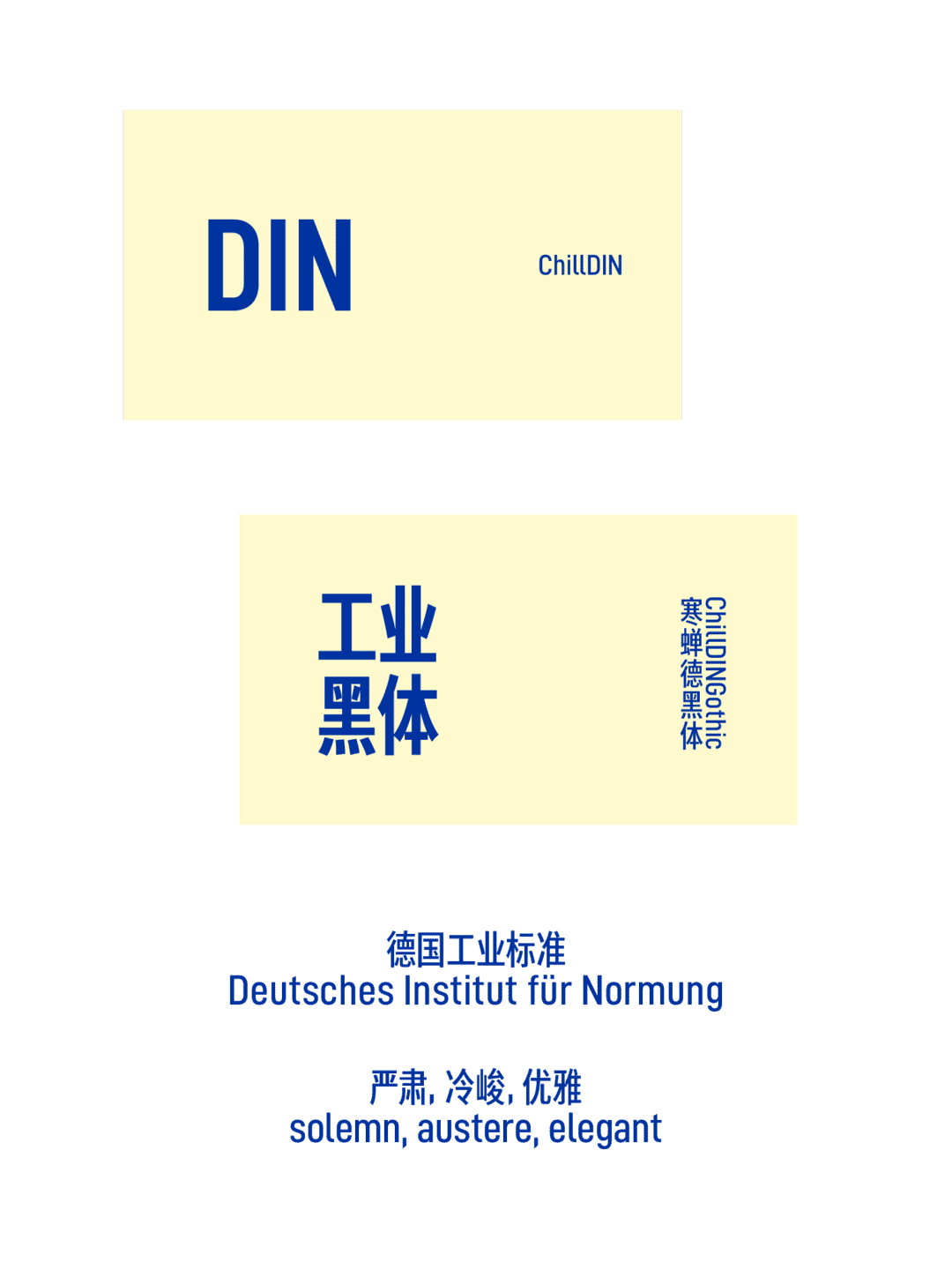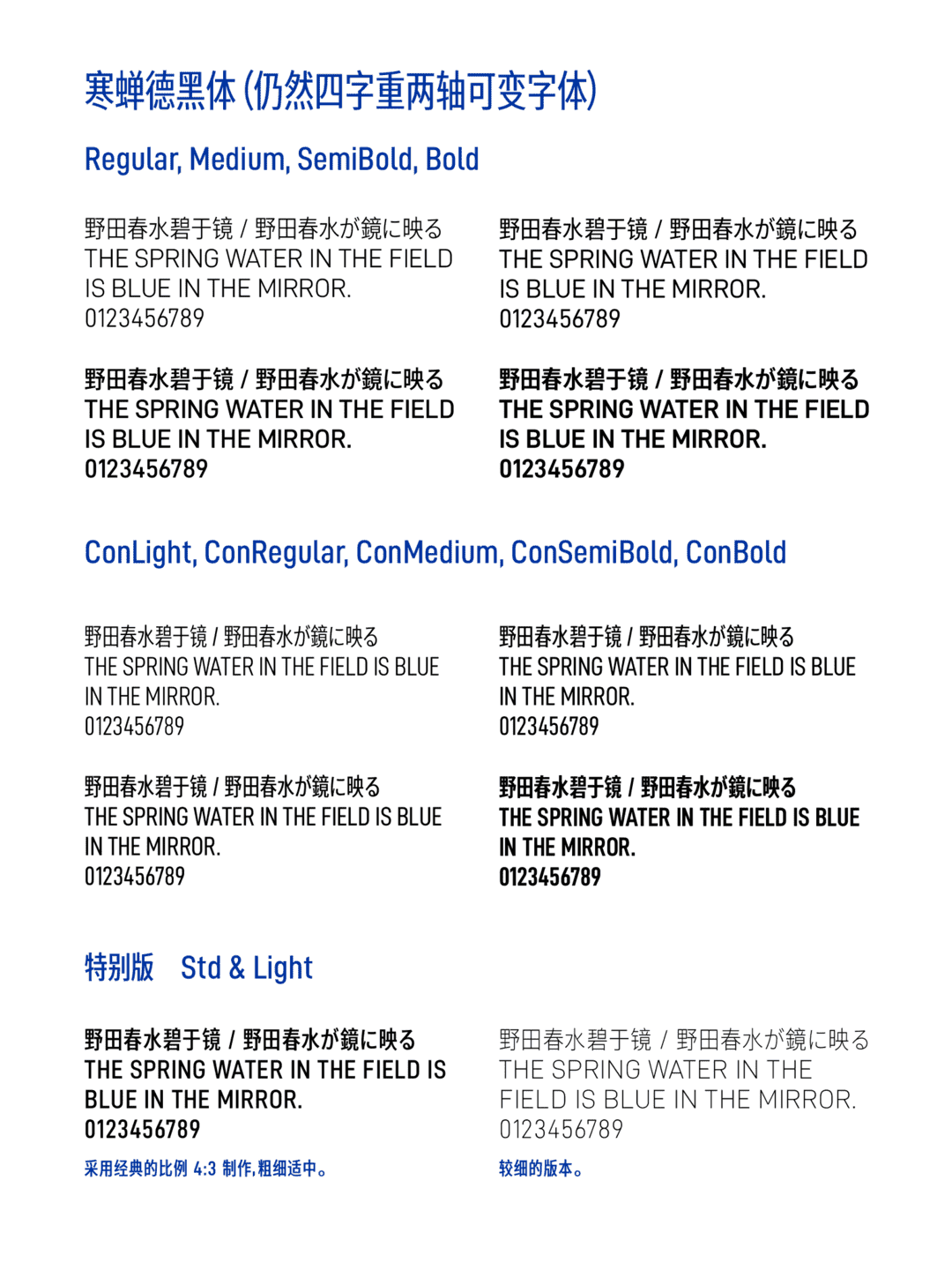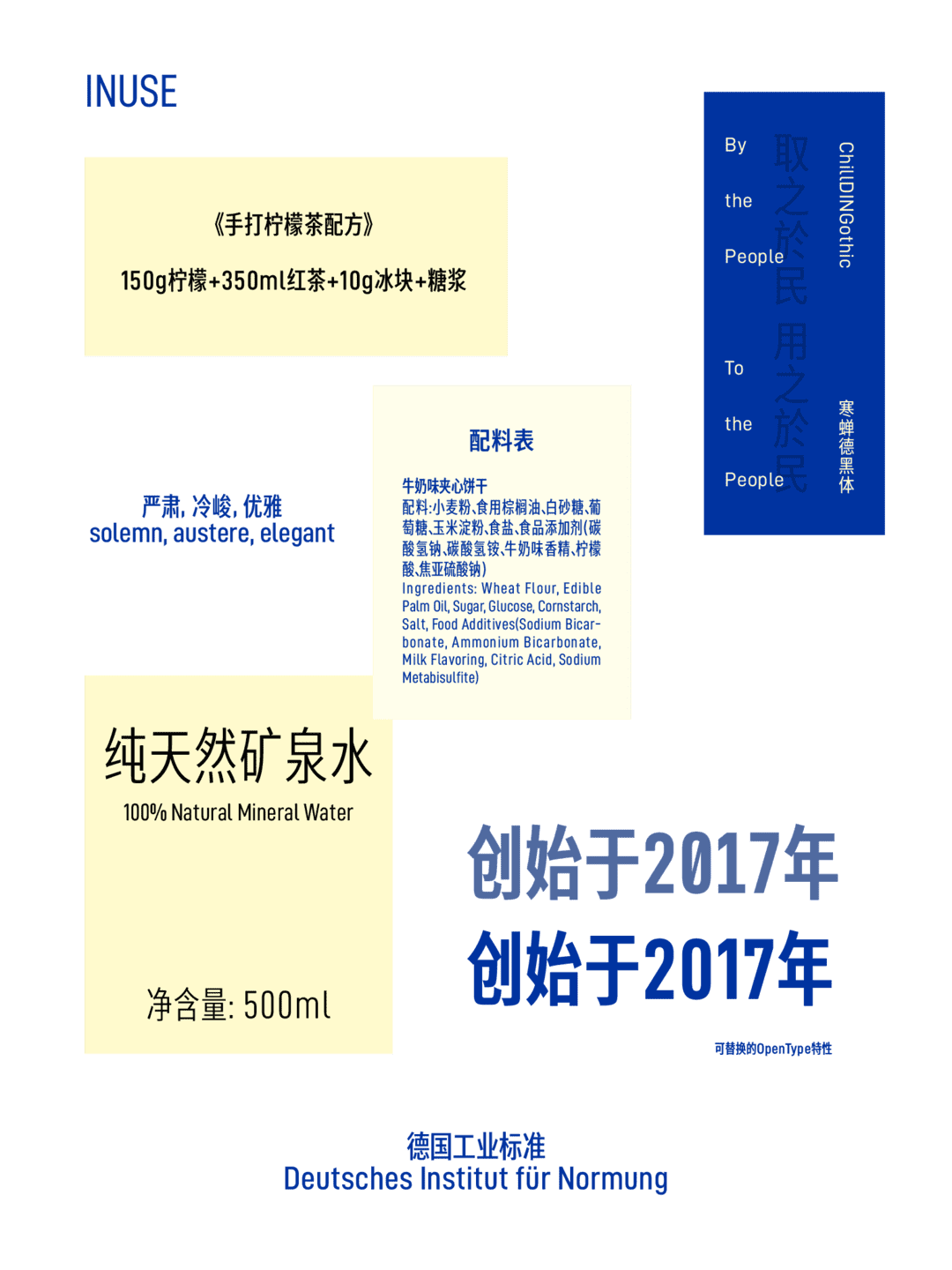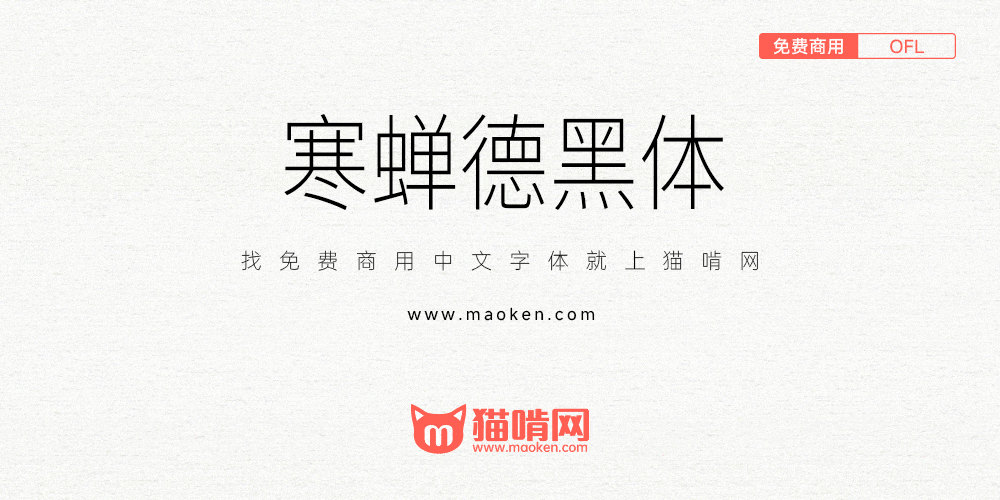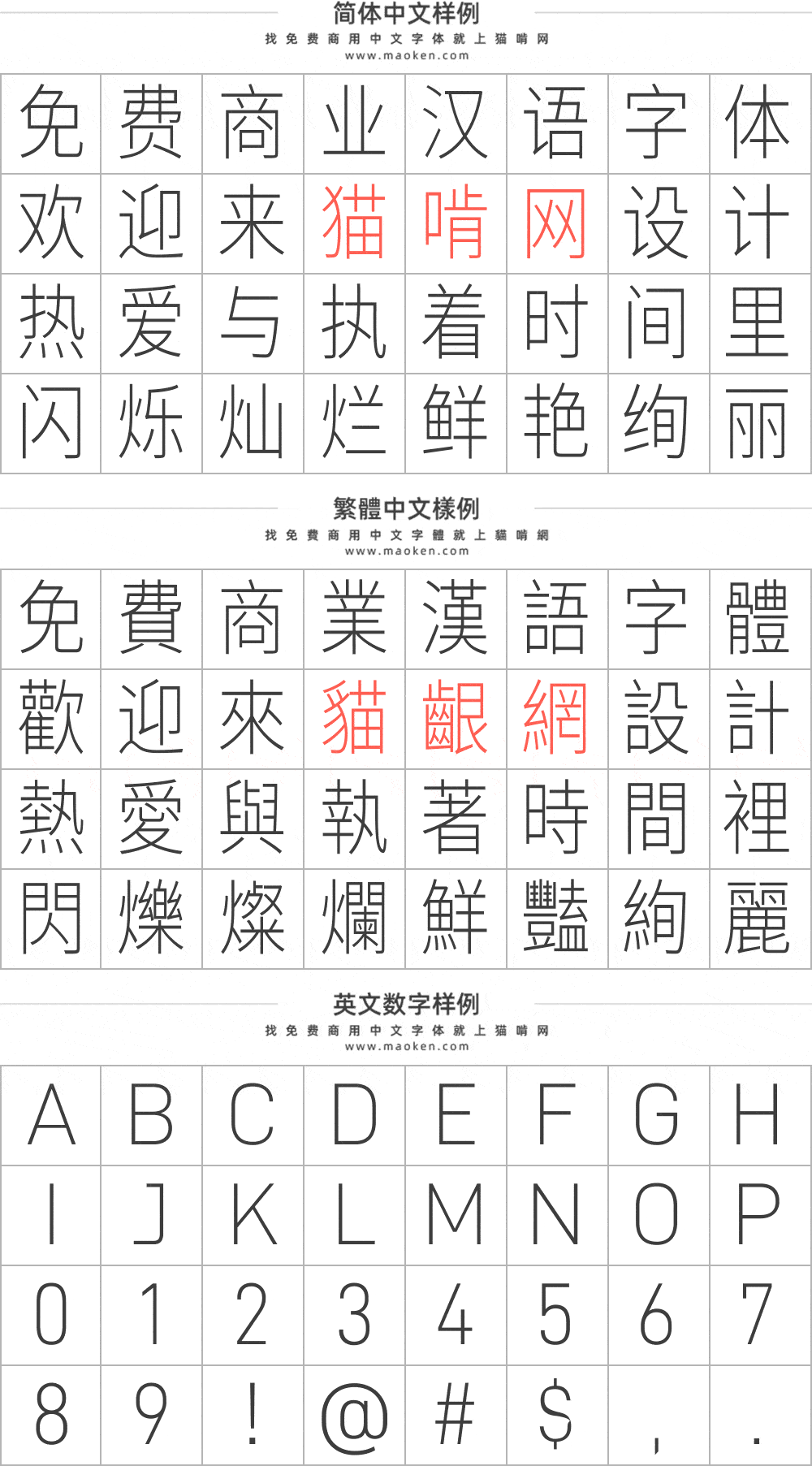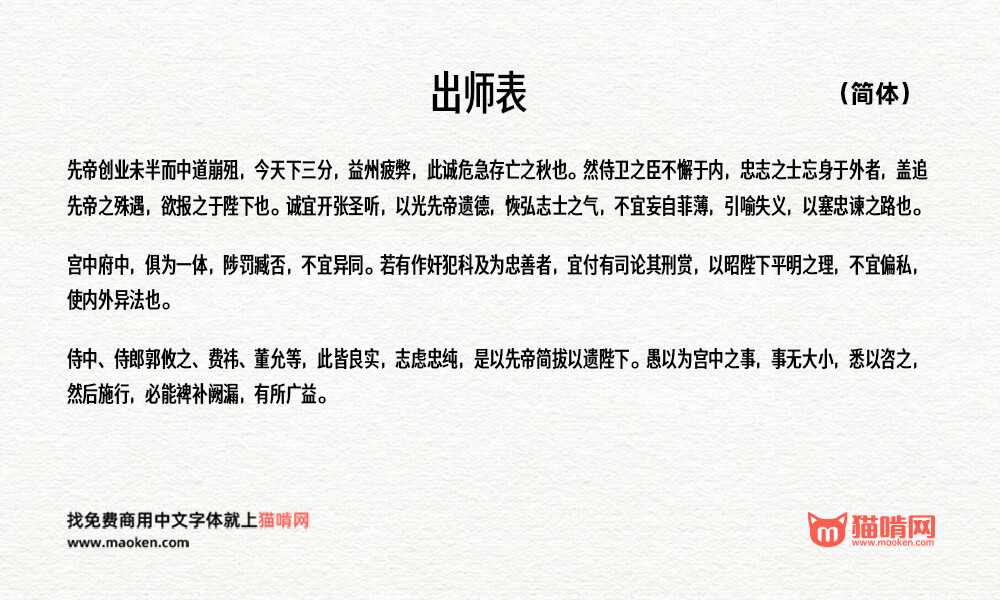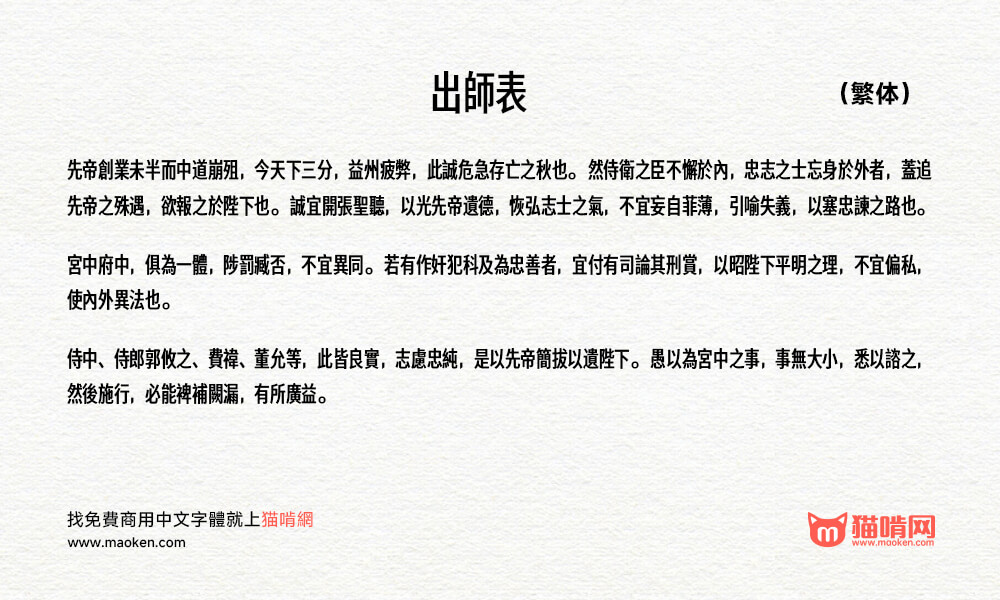
寒蝉德黑体:源于德国工业标准字体“DIN” 基于D-DIN的修缮
字体作者:寒蝉字型 (中国大陆) 字体字重:5个
ChillDIN与寒蝉德黑体。源于德国工业标准字体“DIN”,基于D-DIN的修缮。中文字体的搭配从来源寒蝉端黑体(思源黑体),修改了参数和标点融合。
上标、下标数字不全,希望作者修复
没有全角:冒号
• 实际上1.2版也没有全角数字,1.3甚至比1.2缺字更多,我已告知作者,没收到回复。
这个字体非常好,这种瘦长的黑体特别地清新,但不知道为什么,我运用到oneui,有一些字在黑体状态下呈现的是三星自己的字体,而且音标不能正确显示。但这款字体整体上非常棒
字体效果很不错,用来模仿国内车牌的字体非常合适
截至v1.200:
1. 猫啃预览图可见至少英文“$”曲线有错,除粗体外全部字重包括可变皆是,原作无此问题,应该是修改时误动了锚点。
2. Light的西里尔文很糟、上下标过粗、“◌̉”反常,应该是反推细体的问题。
3. 有约170个替换字形未被使用无法调取,来自思源或D-DIN?显然丢失了相关特性。
4. “`”有问题。
另外“%”不应支持斜杠〇样式,虽然可以理解是为了区分“⁰⁄₀”(?)但太黑了,我提议.ss06修改如下:
%⁰⁄₀仍然可以区分也更“DIN”。另外像是“tt”连字是多余的,完全没有效果。